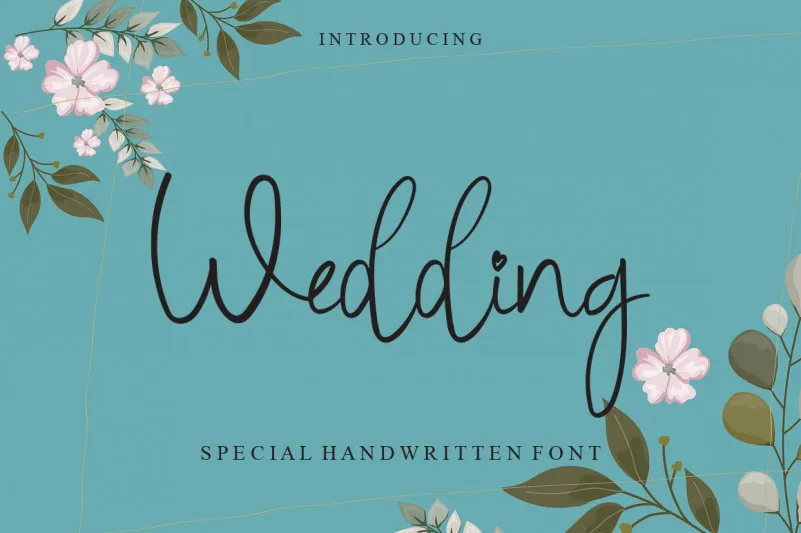
Wedding Cursive Handwritten Font – Download Grátis
Esta Wedding Cursive Handwritten Font é perfeita para quem busca uma fonte que transmite autenticidade e encanto através do seu trabalho manual. Suave e fluida, ela se destaca não apenas como uma escolha ideal para cartões de agradecimento ou estampas personalizadas, mas também como um recurso versátil para criações branding ou etiquetas. Seja você um criador de arte ou designer gráfico, essa fonte cursive é capaz de enriquecer seus projetos de forma única e sofisticada, adicionando um toque especial a qualquer ideia de crafting que você possa ter em mente. Aprecie o encanto da natureza nas palavras escritas com cuidado, transformando pequenas cartas em mensagens verdadeiramente únicas.